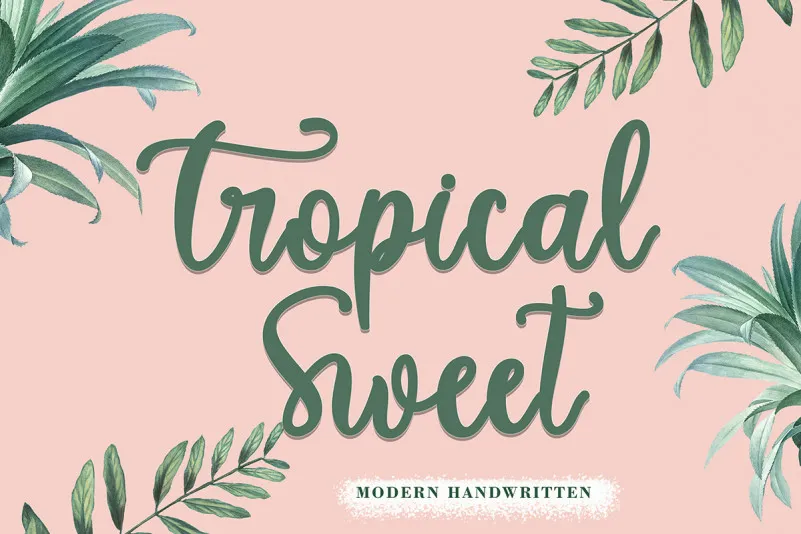
Tropical Sweet Font
A Tropical Sweet Font é uma trama delicada e fluida criada pelo Designer Yoga Letter, perfeita para aqueles que desejam dar vida aos seus projetos com um toque irresistivelmente tropical e suave. Com traços elegantes e movimentos curvos que se parecem mais com gorgonzolas doce e frutas tropicais em flores, esta fonte é uma ótima escolha para criar designs de alto nível e charme. Ideal para aqueles que buscam um visual atraente sem comprometer a legibilidade, Tropical Sweet pode ser facilmente adaptado aos estilos dos seus projetos, seja eleve os elementos gráficos de forma criativa ou adicione um toque romântico ao seu conteúdo. Aproveite as oportunidades para criar designs únicos e memoráveis com esta fonte que transborda alegria e frescor tropical em cada letra.